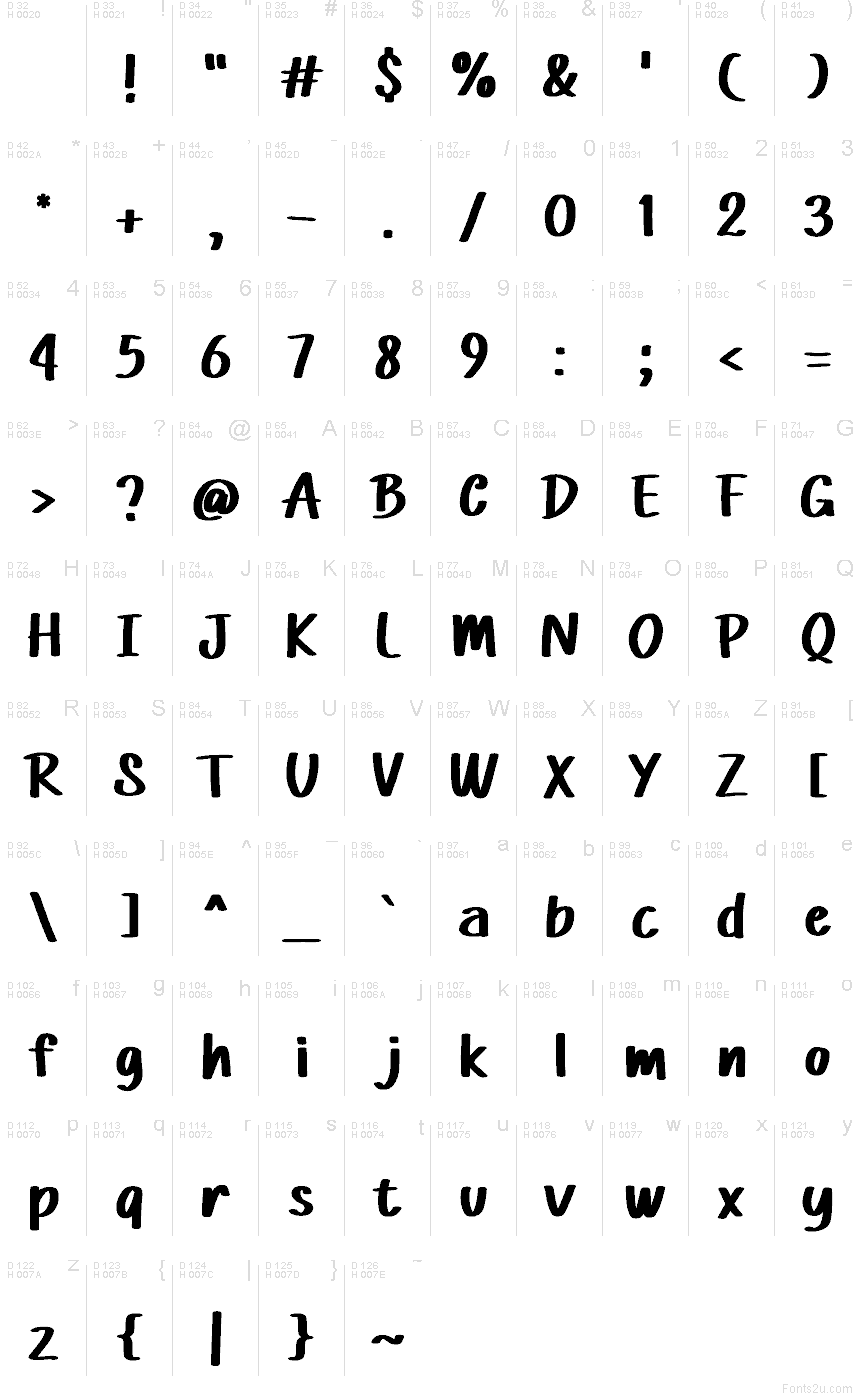
Rain Cartoon
Rain Cartoon від студії Hello Good — це безкоштовний рукописний шрифт із широкими заокругленими штрихами та вільним, «мальованим» ритмом. Форми літер нагадують написи, зроблені маркером або пензлем, а завдяки плавним з’єднанням і простим контурам дизайн виглядає дружнім і невимушеним, не втрачаючи при цьому охайності.
Rain Cartoon чудово підходить для дитячого пакування, меню кав’ярень, заголовків на постерах, листівок та графіки для соцмереж, де особистий рукописний акцент допомагає зробити текст менш формальним. Цей безкоштовний шрифт також добре пасує до грайливих логотипів та коротких цитат, адже його заокруглені форми та легкий ритм додають тексту теплого та спокійного настрою.